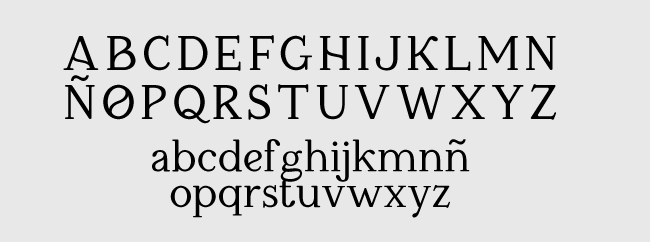
Una de sus características es las pequeñas ligaduras o curvaturas en algunos trazos de las letras de caja alta, lo que aporta una personalidad que no muchas tipografías tienen.
Inji Kristján es un diseñador gráfico islandés afincado en Berlín. Éste proyecto fue creado como parte de un taller sobre creación de tipografías impartido por la Academia de Artes de Islandia, en 2012.
One of its characteristics is the small ligatures or curvatures in some strokes of the letters of high box, what contributes a personality that not many typographies have.
Inji Kristján is an Icelandic graphic designer based in Berlin. This project was created as part of a workshop on typography creation given by the Icelandic Arts Academy in 2012.